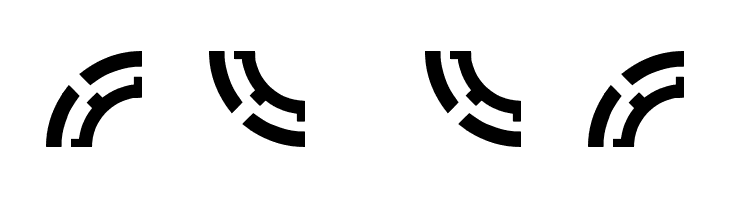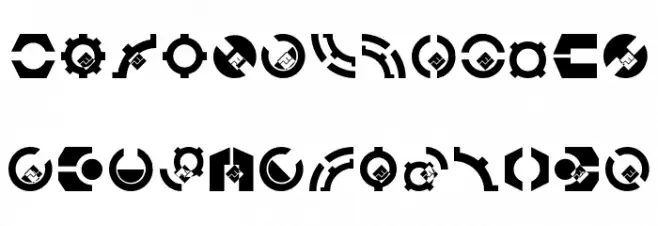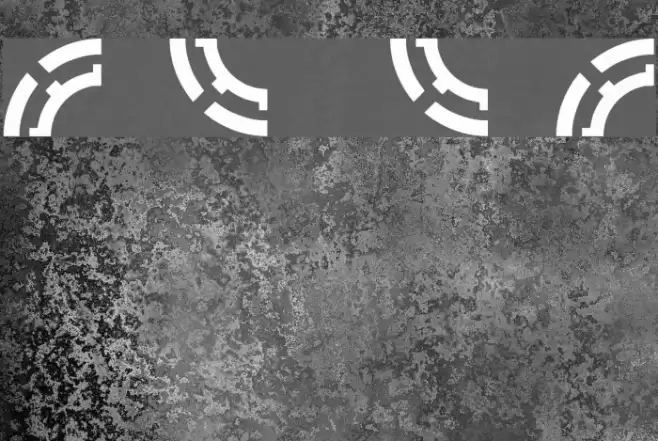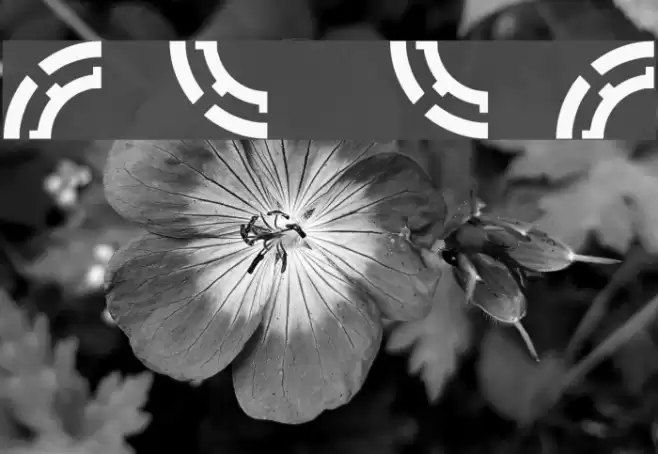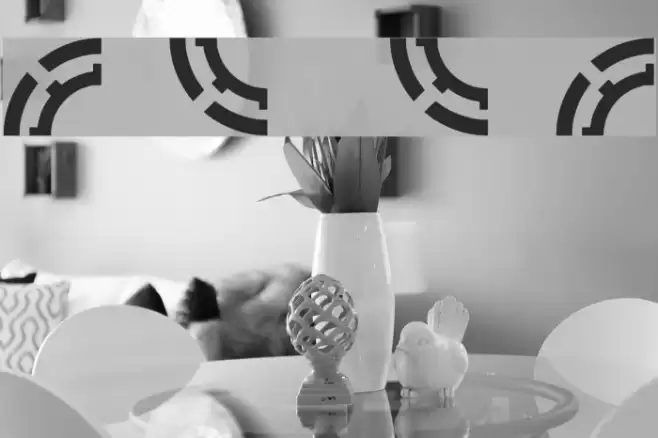
The Genius and Galactic Things Font
| Gesamtstil | Futuristic, Sci-Fi |
| Anwendungsfall | Logos, Titles, Decorative elements |
| Vorgeschlagene Projekte | Ideal for use in sci-fi themed games, movies, or books as an alien language or code. Could also be used in branding for tech companies or futuristic products. |